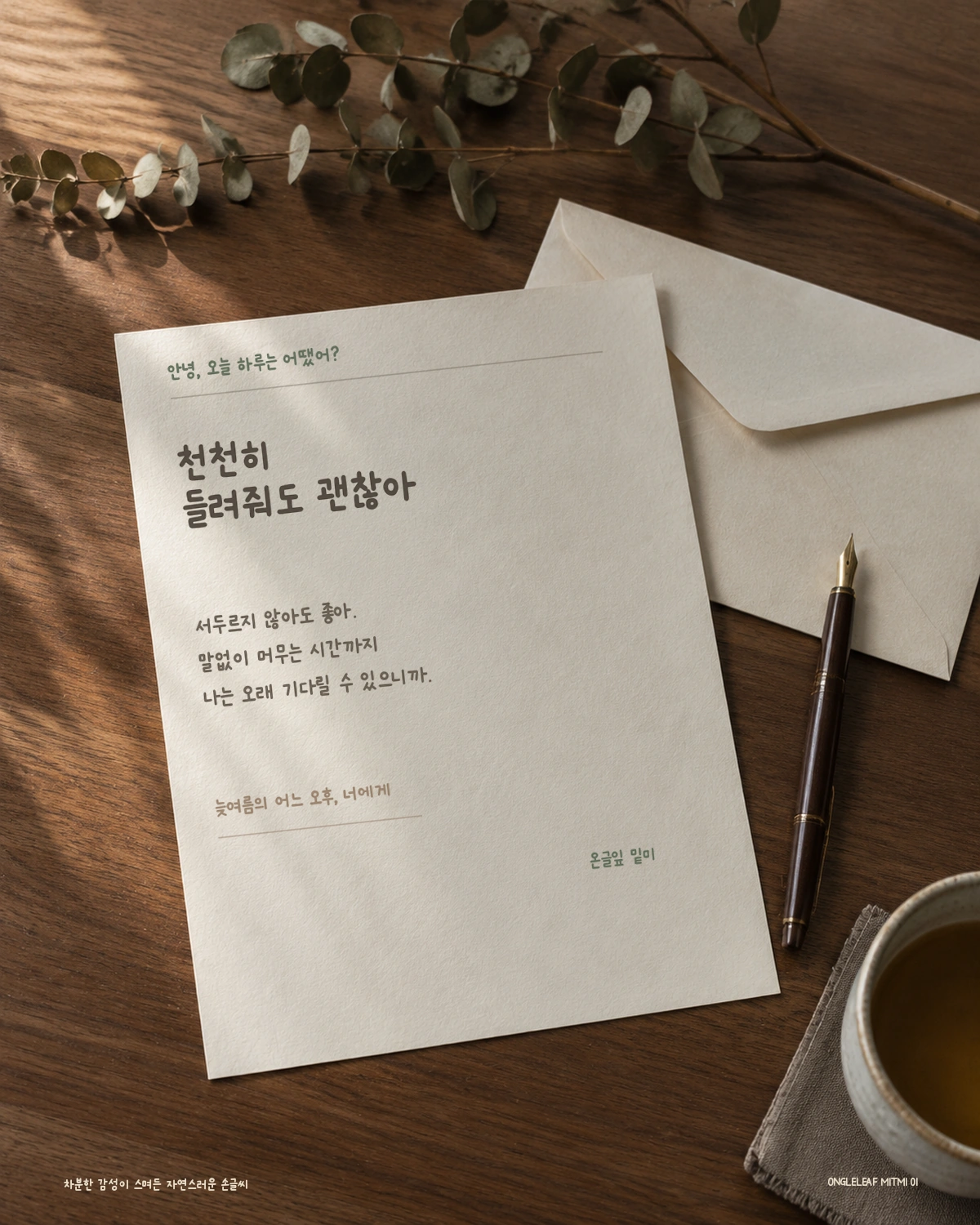
온글잎 밑미 — 밑미 X 보이저엑스에서 배포하는 무료 폰트입니다. 뉴스레터에 손으로 적어 온 글씨에서 온 서체로, 차분하고 자연스러운 결이 살아 있는 손글씨체
자아성장 큐레이션 플랫폼 밑미가 보이저엑스와 함께 만들어 2023년 12월에 공개한 손글씨 서체입니다. 배포 경위가 특이합니다. 원래 밑미가 사내에서만 쓰던 폰트를 연말에 커뮤니티에 선물로 푼 것입니다.
글씨 주인도 밝혀져 있습니다. 밑미팀 디자이너 루시 님인데, 공개하면서 남긴 글이 이 서체의 성격을 잘 설명합니다. 밑미레터에 쓰는 글씨는 대부분 손으로 쓰는데, 활자에 사람 냄새나는 밑미의 목소리를 담고 싶고 문장이 리드미컬하게 읽혔으면 좋겠다는 마음 때문이라는 것입니다. 다만 분량이 많거나 자리를 비울 때는 손으로 쓸 수 없어 인공지능으로 만든 폰트의 힘을 빌린다고 덧붙였습니다.
조형도 직접 설명해 두었습니다. 직접 쓰는 것보다 문장이 단정하게 읽히지만 손글씨 특유의 느낌을 잃지 않아 다양한 곳에 쓸 수 있다는 것입니다. 온글잎 계열 여섯 종 가운데 제작사가 조형을 직접 설명한 유일한 서체입니다. 권하는 자리도 적어 두었습니다. 기록을 남기고 싶을 때, 내 기록에 활기를 더하고 싶을 때 자유롭게 쓰라는 것입니다.